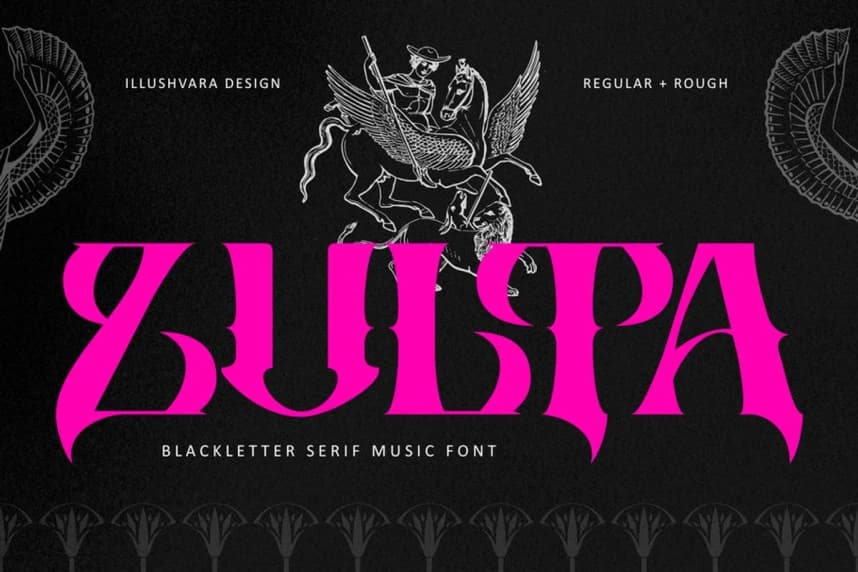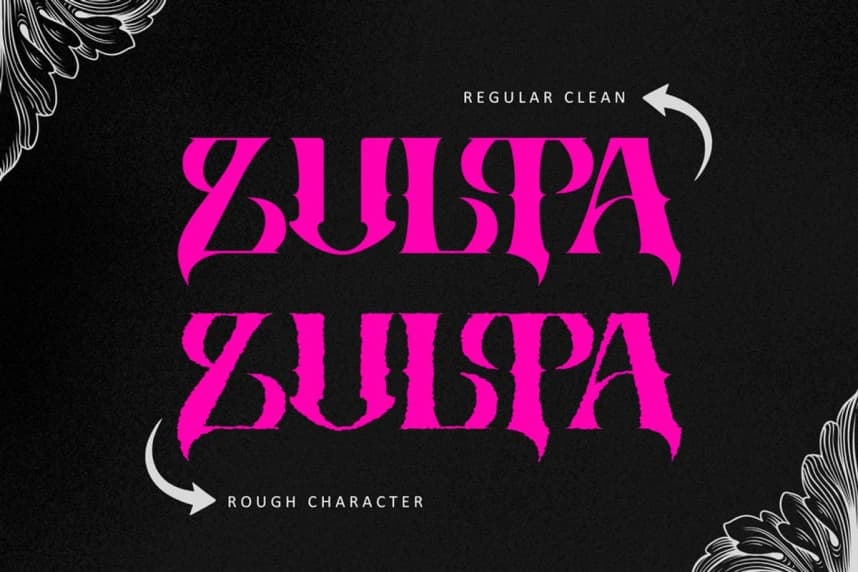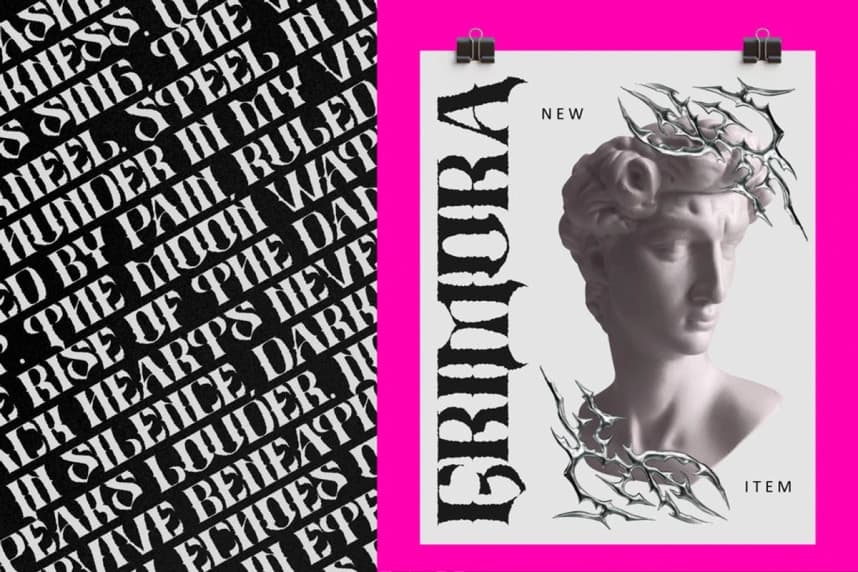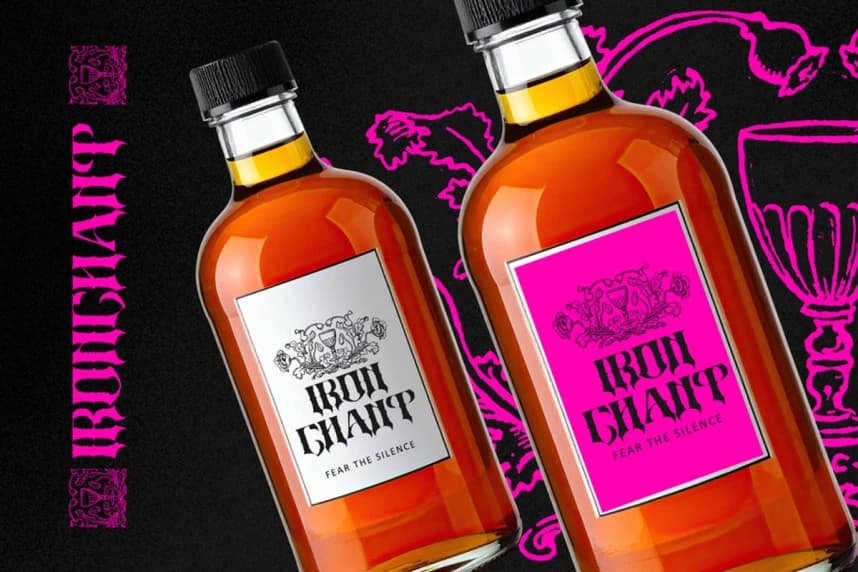
Zulta Music Yazı Tipi
Zulta Music Font, keskin serifli tüm harflerden oluşan ve güçlü gotik enerji veren kalın bir blackletter yazı tipi ailesidir. Regular ve rough stillerde mevcuttur; bu yazı tipi metal müzik tanıtımı, albüm kapakları, grup ürünleri ve posterler için tasarlanmıştır.
Zulta Music Font, keskin serifli, tüm harfleri büyük olan, güçlü gotik enerji veren cesur bir blackletter yazı tipi ailesidir. Normal ve pürüzlü stillerde mevcuttur; bu yazı tipi metal müzik tanıtımı, albüm kapakları, grup ürünleri ve posterler için tasarlanmıştır.